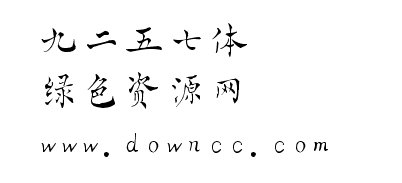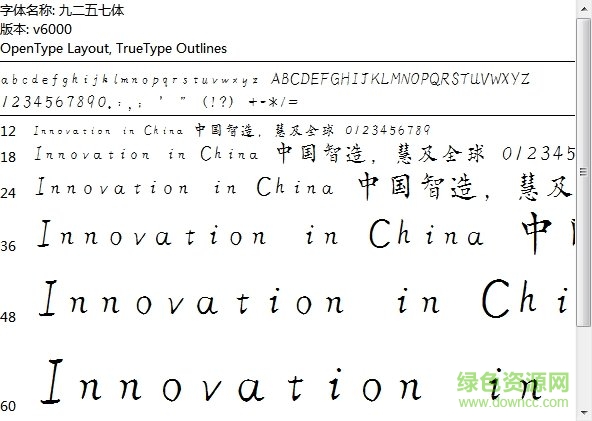
九二五七體是喻東山創(chuàng)作的一款個(gè)性手寫(xiě)書(shū)法字體,造型優(yōu)雅,兼具毛筆書(shū)法字體的飄逸、顏體的秀美,給你高潔大氣的視覺(jué)呈現(xiàn),喜歡的朋友就來(lái)綠色資源網(wǎng)免費(fèi)下載吧!
九二五七體(毛筆)字庫(kù),有柳體的秀逸,顏體的彈性,褚體的纖細(xì),歐體像左上的挺拔。
九二五七體別具一格,字跡飄逸灑脫,結(jié)構(gòu)寬松得體,行筆流暢而筆觸凌厲張揚(yáng),具有不錯(cuò)的古風(fēng)韻味,給你的平面設(shè)計(jì)、海報(bào)設(shè)計(jì)、包裝設(shè)計(jì)等帶來(lái)不錯(cuò)的藝術(shù)體驗(yàn)!